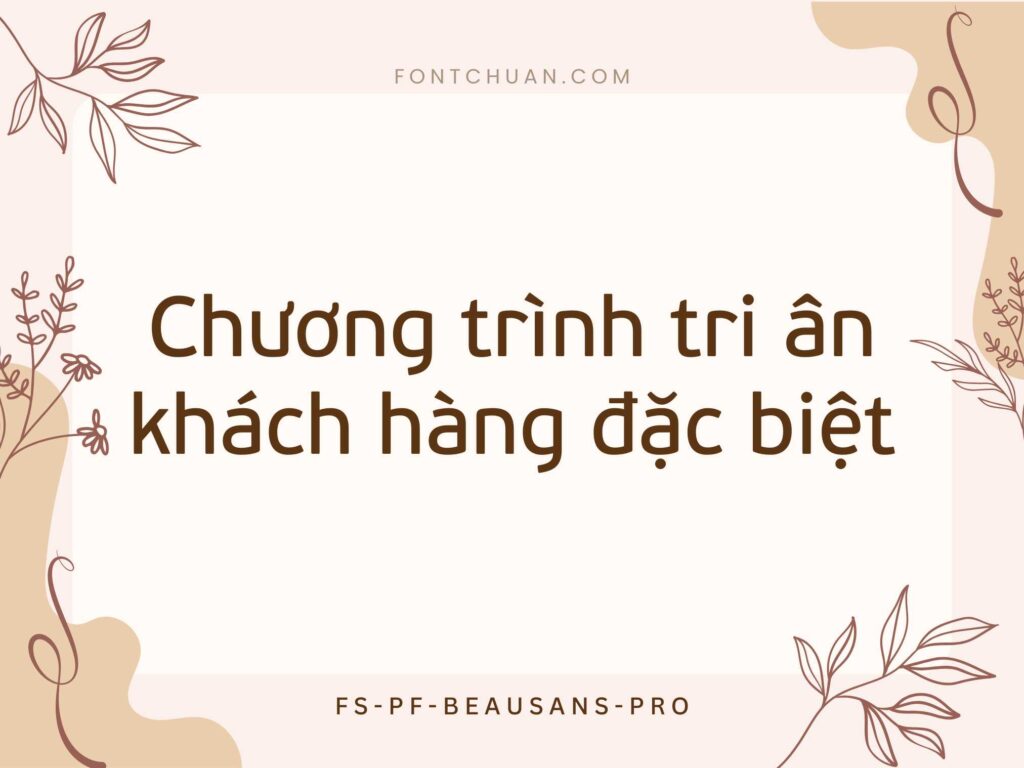
Font FS Pf Beausans Pro Việt Hóa
Tác giả Font: Panos Vassiliou
PF Beau Sans Pro là một họ phông chữ sans-serif hiện đại, được thiết kế bởi Panos Vassiliou và phát hành bởi Parachute vào năm 2002. Lấy cảm hứng từ Bernhard Gothic, một trong những sans-serif hiện đại đầu tiên của Mỹ do Lucian Bernhard thiết kế vào cuối những năm 1920, PF Beau Sans Pro mang đến sự kết hợp giữa phong cách cổ điển và hiện đại. Với sự Việt hóa của Phông Chữ Việt, phông chữ này hỗ trợ đầy đủ các ký tự tiếng Việt, giúp người dùng dễ dàng áp dụng trong các thiết kế đa ngôn ngữ. Thành viên của Font Chuẩn đã sưu tầm và chia sẻ phông chữ này nhằm đáp ứng nhu cầu của cộng đồng thiết kế.
Về đặc điểm thiết kế, PF Beau Sans Pro bao gồm 16 kiểu chữ với các trọng lượng từ ExtraThin đến Black, cùng với các phiên bản nghiêng tương ứng. Phông chữ này hỗ trợ ba hệ chữ chính: Latin, Hy Lạp và Cyrillic, phù hợp cho nhiều ngôn ngữ khác nhau. PF Beau Sans Pro đặc biệt thích hợp cho các dự án thiết kế như thương hiệu, thiết kế biên tập, giao diện người dùng và các ấn phẩm quảng cáo, mang lại sự chuyên nghiệp và tinh tế cho thiết kế. Ngoài ra, phông chữ này cũng phù hợp cho các sự kiện như lễ hội, sinh nhật, Valentine và Trung thu, tạo không khí ấm áp và gần gũi. Trong lĩnh vực ngành nghề, PF Beau Sans Pro được ứng dụng rộng rãi trong quảng cáo, thiết kế thiệp cưới, giáo dục và công nghệ, góp phần tạo nên sự độc đáo và thu hút cho các sản phẩm và thương hiệu.